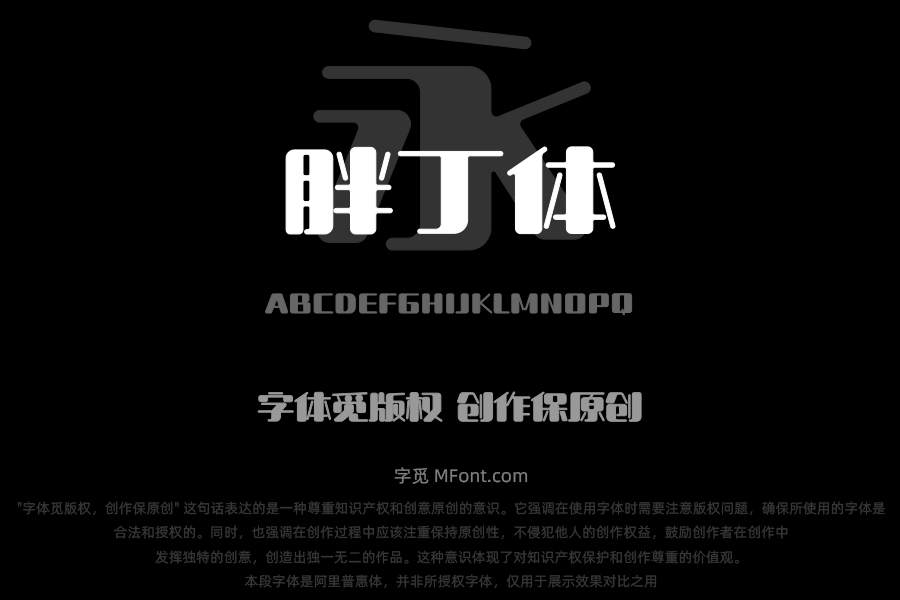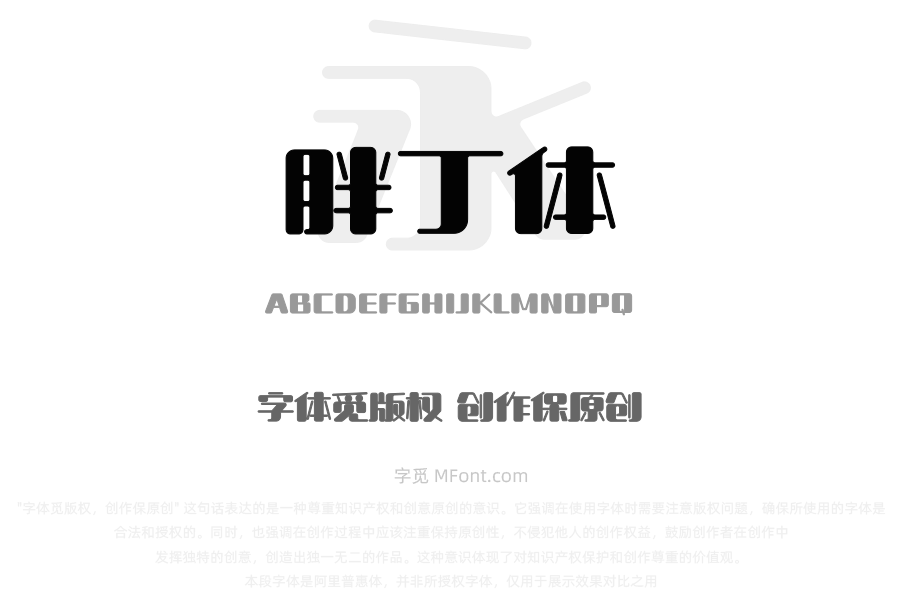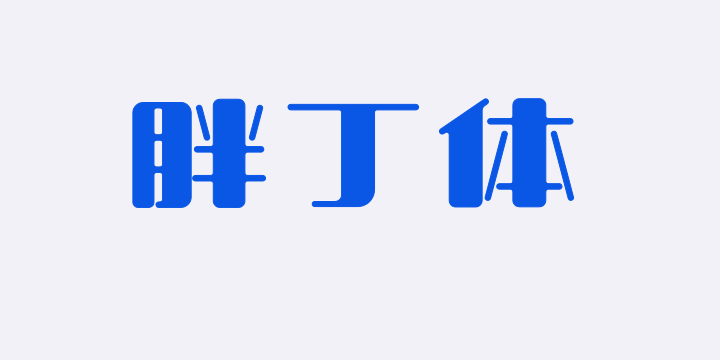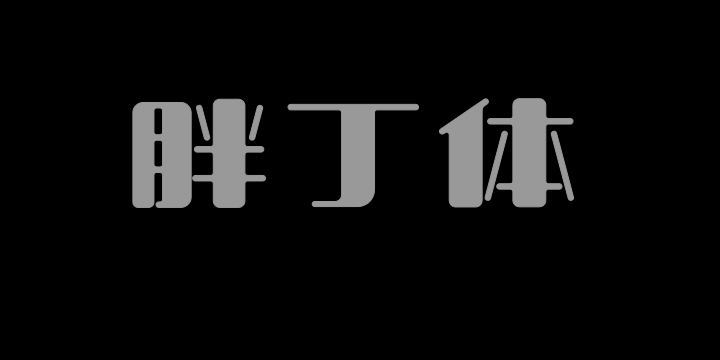
• 上首胖丁体
字体全名: 上首胖丁体
字体简介: 上首胖丁体,简体中文约6763字,字体整体方正,但在笔画上采用强烈的粗细对比,且在笔画以及其连接处做了倒圆处理,使得字体比较卡通活泼,其中极粗的竖笔使得字体看起来敦实可爱。设计强调几何化处理,减少笔画细节,突出核心信息。字体偏向于卡通、可爱的风格。字体特点鲜明,适用于搭配标志、广告标语、商业广告、海报字体等高端属性。